辞典、文件、报刊书籍……目所能及之处的汉字存在,就像我们身边的空气一样自然。但是,我们或许从未考虑过这些字体从何而来?又是怎样从手写变成印刷的?今天揭幕的“现代汉字印刷字体发源地”和“上海印刷字体展示馆”,场馆虽然“迷你”,却可以让更多人了解现代汉字印刷字体的起源和发展,了解汉字印刷字体的设计规范和创写工艺,更好地宣扬与传承汉字文化、字体文化、非遗文化。
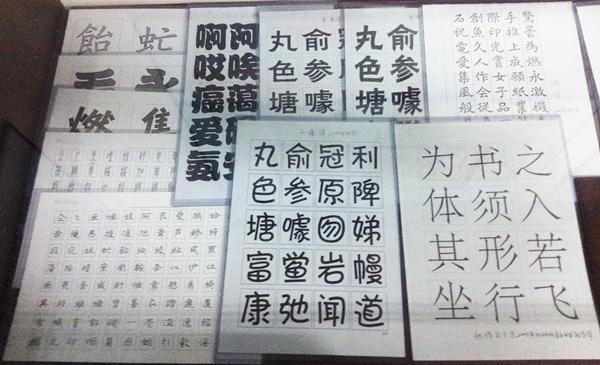
图说:你了解字体吗?
四种字体诞生源头
“现代汉字印刷字体发源地”和“上海印刷字体展示馆”都位于新闸路1209弄60号上海印刷技术研究所中,新中国的印刷字体就诞生于此。
在相当长的一段时期内,我国汉字的字体、字形杂乱,异体、变体混合使用,严重影响印刷质量和阅读效果,更导致我国参加国际书籍装帧博览评比无功而返。1959年,文化部召开会议指导上海率先进行“印刷字体改革”,以印研所为基地,在新闸路1209弄60号内集聚了沪上美术创意有功力、书写正楷有造诣、雕刻字模有经验的三结合人才,成立了由50多人组成的字体研究室。印研所字体研究室的设计人员耗时5年,相继完成了宋、黑、楷、仿四种常用印刷字体的创写设计,总计8万字,为新中国推广简化字和汉字使用的规范化作出了巨大的贡献。
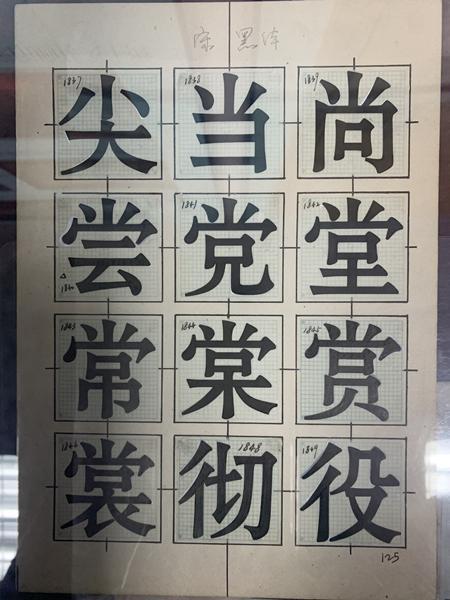
图说:黑体
其中,宋体吸取《燕子笺》等古代版本和近代宋体字之长,融合书法、美术和刻字的创意灵感和艺术韵味。黑体多用于标题,有时夹排于正文,字形方中带长、黑白匀称、行款整齐,并加以喇叭口装饰,端庄稳定。楷体于1964年完成设计,横划倾斜,竖划斜直不一,笔划粗细起伏,笔形流畅自然,是初学汉字的首选字体,主要用于排印小学教科书和少儿读物。1965年完成的仿宋体,笔形挺秀,横竖划粗细接近,结构兼有楷宋特点,竖划收笔有垂露顿角,主要用于文件正文。
电脑字库原创母体
20世纪80年代,上海印刷技术研究所将宋、黑、楷、仿四大品种的专用字稿作为同英国蒙诺公司合资的投资,首次购进国际先进的激光照排设备。后又将这四种字体的原始字稿,全部复印无偿提供给国家“748”工程、“汉字信息处理”重大项目,为我国印刷业实现告别“铅与火”的技术革命作出了贡献。北大方正的王选教授将这些字体与现代数字信息技术相结合,成为发明“汉字信息处理激光照相排字技术”的原创母体,之后普遍进入海内外汉字字库,派生再造出千姿百态、各有特点的后代字体。
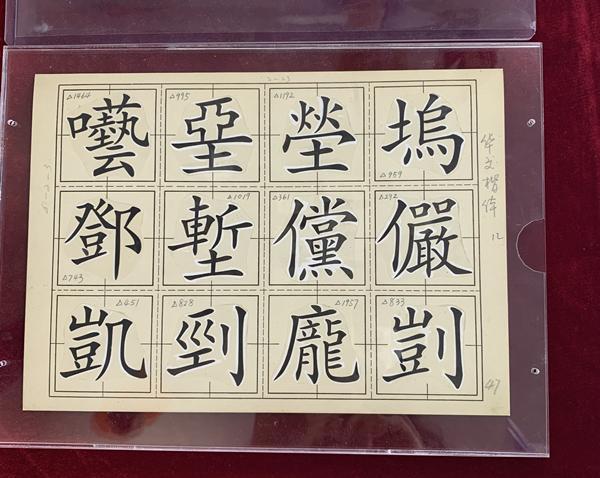
图说:华文楷体
目前国内普遍应用在计算机系统字库里的宋、黑、楷、仿四副常用字体品种,无论是国标字数的增加还是品种的扩展,它们的笔形、结构、重心、粗细等内外形基本框架及其神韵,都源于上世纪上海印刷技术研究所创写的印刷字体。
书写技艺代代相传
2009年6月,印研所“汉字印刷字体书写技艺”项目,被列入第二批上海市非物质文化遗产项目名录,研究所现有非遗传承人十余位,在今年上海书展上发布的新版《辞海》所使用的三套字体就是由上海印刷技术研究所创写的辞海宋、辞海黑、辞海中黑。
第二代传承人陈其瑞生于苏州,15岁来上海读书,18岁进了上海印刷技术研究所(简称印研所)的活字字体研究室,这位当年最年轻的字体设计师,如今已是古稀之年。
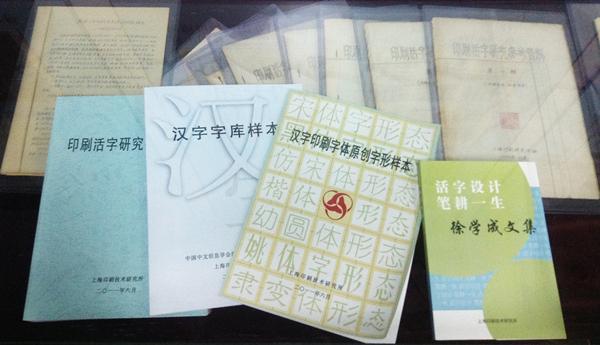
图说:各种字体样本集
陈其瑞从事字体设计的时期,正赶上新中国成立后铅字印刷的“黄金时期”。“要设计出一个字,是很不容易的,过程很枯燥。首先得打铅笔稿、复制正稿,然后用直线笔画线,再用毛笔勾描点、撇、捺、勾,之后再将空心字填墨,接着描白。拍照缩小样后,还要对字体的结构、大小、粗细、笔形进行修整统一。我们几个人分工做,像流水线工作那样,平均算下来,1个人一天最多能写三四个字。”字体设计师必须有书法功底和美术字的书写功底,设计仿宋的钱震之、设计黑体的徐学成和周今才、设计宋体的谢培元和施渭峰……这些大师都是陈其瑞在印研所时的同事和前辈。
如今,第一代传承人都已经作古,但他们留下的手写设计稿依然可以在展示馆的玻璃橱窗里看见,他们设计的字体则几乎随处可见,融入了每个人的日常生活。 (新民晚报记者 徐翌晟)